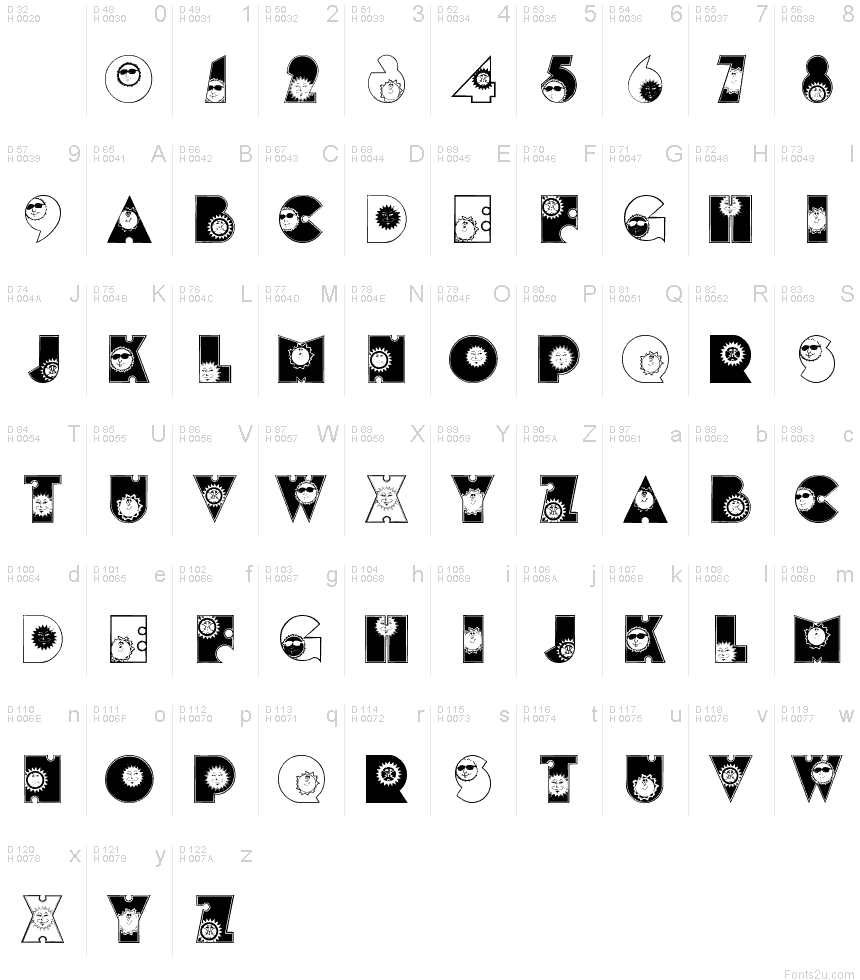
Sunshine Kiddy Font من Lime 2000. graphics هو خط مجاني من نوع dingbat فلكي، يعتمد على تصميمات شموس مبتسمة وأهلة بلمسة طفولية مرسومة باليد. تتكرر الزخارف بحدود سميكة ووجوه بسيطة ونقاط إشعاعية مما يضفي على المجموعة طابعاً مرحاً بدلاً من الطابع الزخرفي المبالغ فيه.